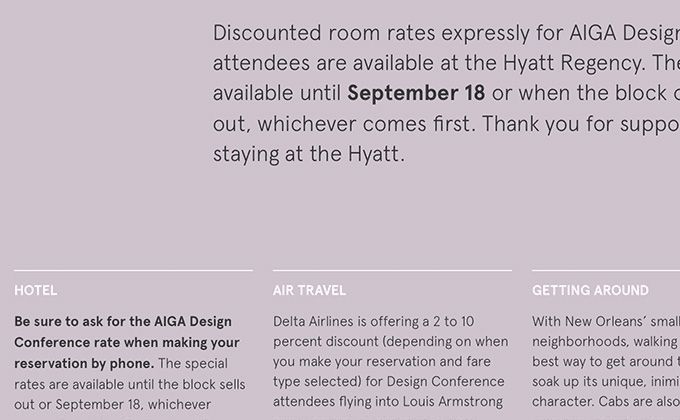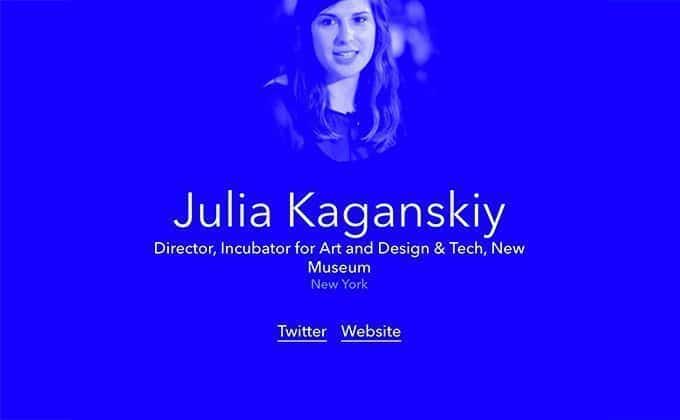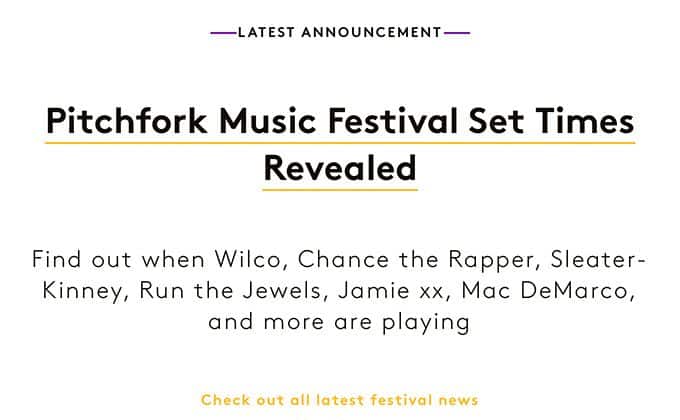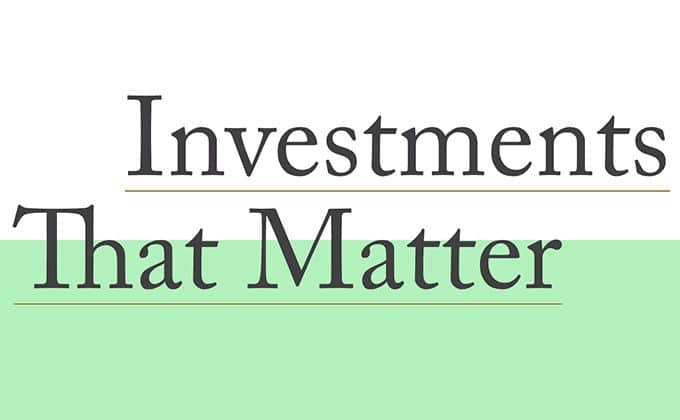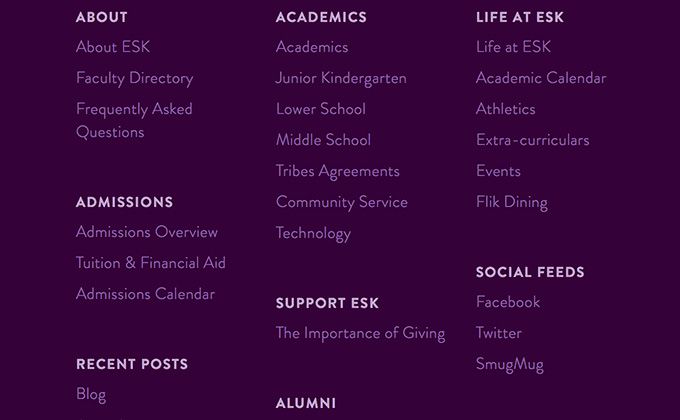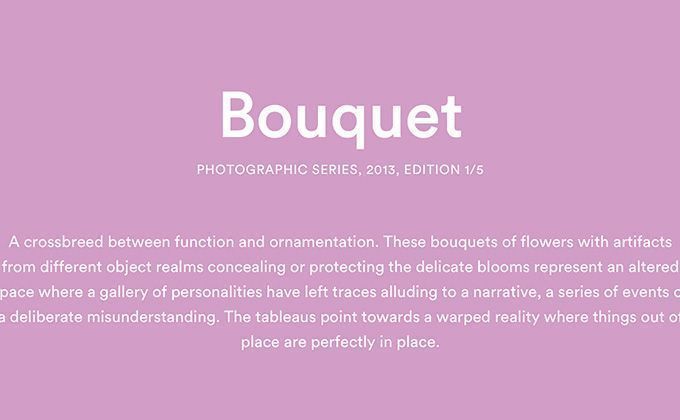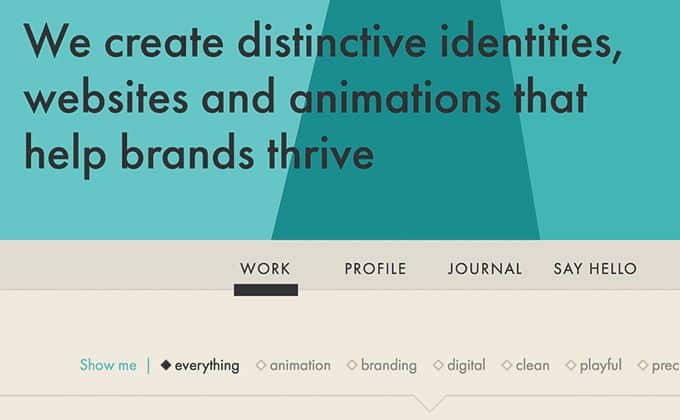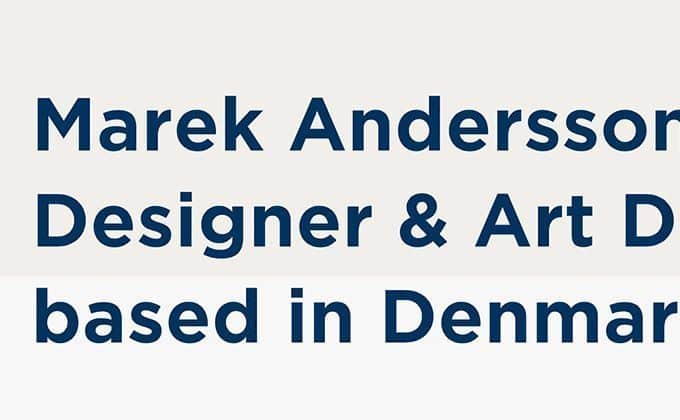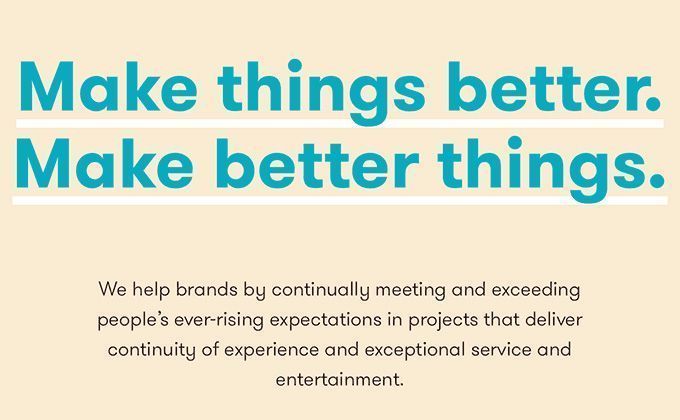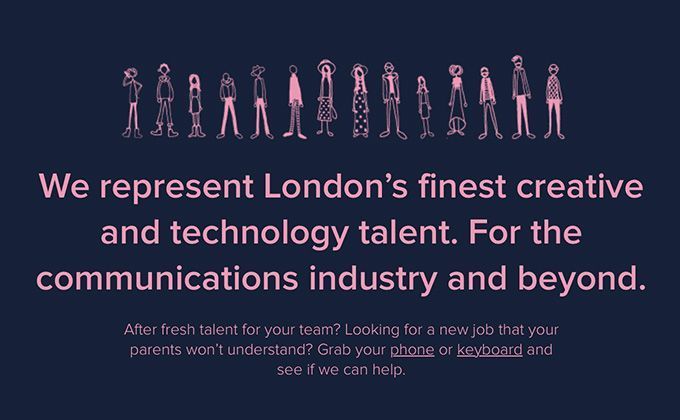
Las 10 tipografías más utilizadas en diseño web
10 tipografías más utilizadas online
Una lista con las 10 tipografías más utilizadas en páginas web
Nos encantan las listas y más si contienen las tipografías más utilizadas en páginas web. Estas son las 10 tipografías que se han utilizado con mayor frecuencia para diseñar webs en todo el mundo. Si quieres algo de ayuda para escoger la tipografía de tu web o simplemente quieres saber qué tipografía es la más utilizada por curiosidad hecha un vistazo a las 10 tipografías más utilizadas en la web, listado realizado por TypeWolf.
10. Circular
Top 10 Mejores Fuentes: Circular
Cuando Spotify hizo rediseño su logotipo, pasó a usar la tipografía Circular en su página web. Todos los comentarios se centraron en comentar el cambio del tipo de verde del logotipo y nadie se fijó en el cambio de uso de tipografía en la web. Gracias al uso por parte de Spotify, la tipografía Circular se convirtió en tendencia y ahora la usan en webs como Airbnb y Menta. Es una tipografía en auge y este 2016 seguro que la vemos en muchos sitios más.
9. GT Walsheim
Top 10 Mejores Fuentes: GT Walsheim
La GT Walsheum es una tipografía que rápidamente se convirtió en tendencia en Londres porque muchos estudios de diseño la utilizaban en su página web. Es una versión más amable de la Futura.
8. Brandon Grotesque
Top 10 Mejores Fuentes: Brandon Grotesque
La tipografía Brandon Grotesque fue la más utilizada el año pasado y aunque este año haya caído hasta la posición 8 es una tipografía muy utilizada en todas las páginas web, desde empresas de hosting a revistas de tecnología pasando por agencias de publicidad. Puede ser que su omnipresencia en la web limite su uso debido a un sobresaturación.
7. Caslon
Top 10 Mejores Fuentes: Caslon
Es la única tipografía con Serif de la lista dominada por tipografías Sans Serif y está como un poco fuera de lugar. Tiene remaches clásicos que gusta a todo el mundo, como la Garamond pero por alguna razón, la Caslon sigue estando año tras año en las listas de mejores tipografías.
6. Avenir
Top 10 Mejores Fuentes: Avenir
La tipografía Avenir es la preferida por muchos diseñadores gráficos. Cada año está en las listas de las mejores tipografías.
5. Brown
Top 10 Mejores Fuentes: Brown
La tipografía Brown es para nosotros la mejor. Elegante y clara es como un mix entre una Futura y una GT Walsheim que se usa en páginas web minimalistas y con un toque de color.
4. Gotham
Top 10 Mejores Fuentes: Gotham
La tipografía Gotham ha ido subiendo en la lista, pasando del 8º puesto el año pasado al 4º este año. Es una de las tipografías más emblemáticas de la última década y es muy popular su uso en las webs actuales.
3. Proxima Nova
Top 10 Mejores Fuentes: Proxima Nova
Proxima Nova es una tipografía que parece que cada año se desinflará y cada año sube posiciones en la lista. ¿Por algo será no? Vemos a muchos son los diseñadores que utilizan esta tipografía.
Web con uso de tipografía Brown | We are move – Donde conseguir tipografía Brown | FontSpring
2. Aperçu
Top 10 Mejores Fuentes: Aperçu
La tipografía Aperçu es un mix de géneros, como una mezcla de la ITC Johnston, Gill Sans, Neuzeit y la Franklin. Es una tipografía popular gracias a que la aerolínea Norwegian Air la utiliza en su web.
Web con uso de tipografía Aperçu | Aiga – Donde conseguir tipografía Aperçu | Colophon Foundry
1. Futura
Top 10 Mejores Fuentes: Futura
Y llegamos al n.1 de las tipografías más utilizadas en la web. Poco podemos decir de la tipografía Futura, una tipografía creada en 1927 que domina la web en 2016. Desde entonces, la tipografía Futura es la reina de las tipografías en la web.